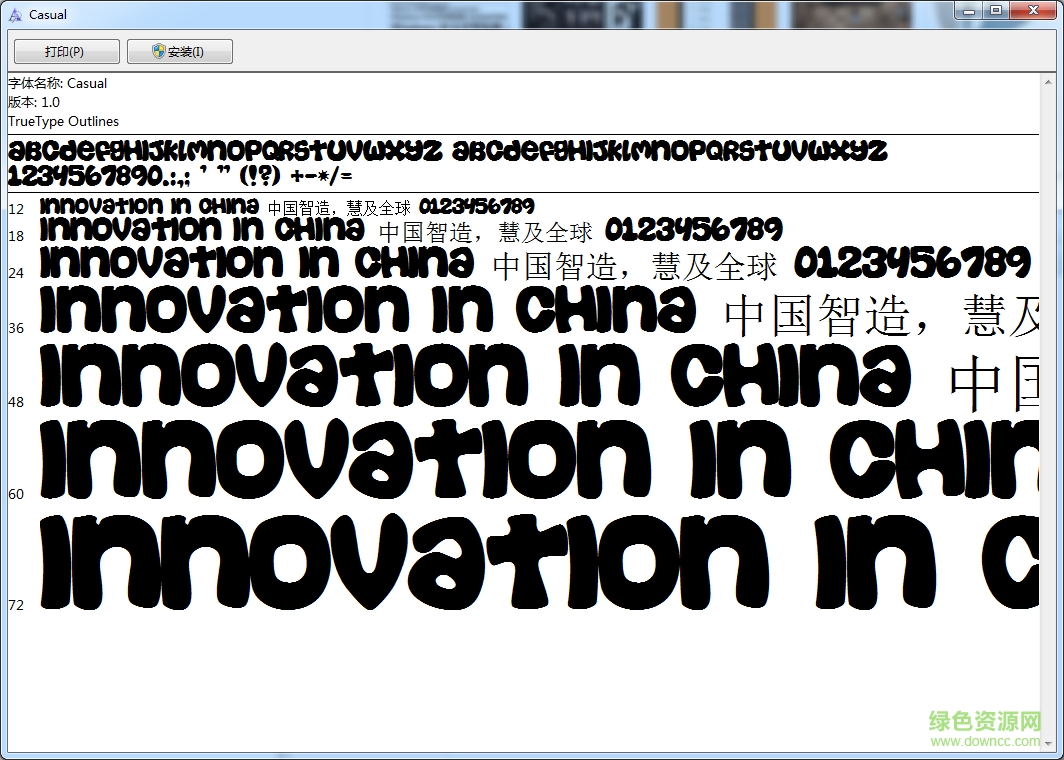
Casual是一款非常常用的英文字體軟件,字體圓潤可愛獨(dú)具特色,字體特色非常的明顯,而且字體看起來十分的落落大方,很適合出版和打印,快速安裝即可使用??靵砭G色資源網(wǎng)下載體驗(yàn)吧!
Casual字體是英文字體庫中的一款字體,Casual字體是一款用于廣告設(shè)計(jì)方面的字體。喜歡或需要此字體的朋友們可以前來下載使用。